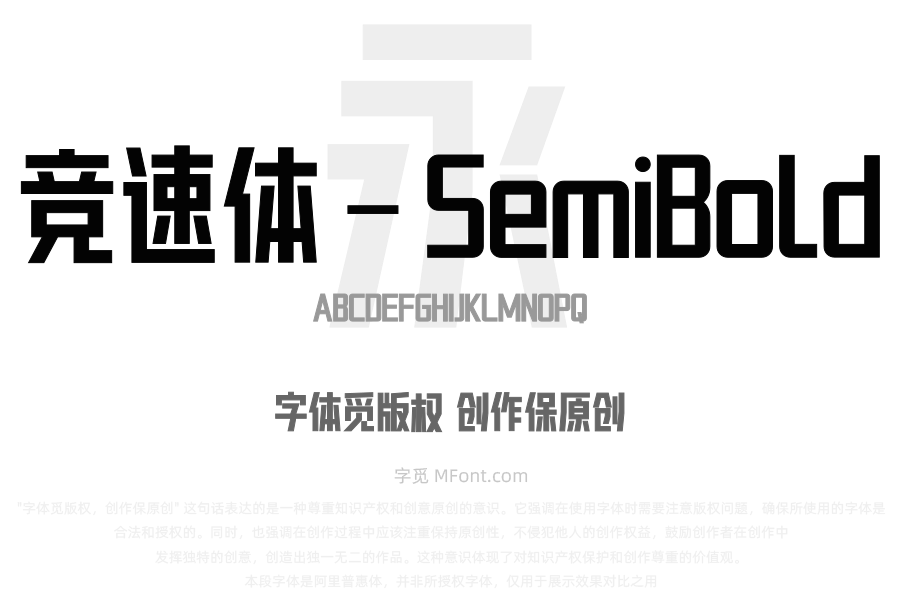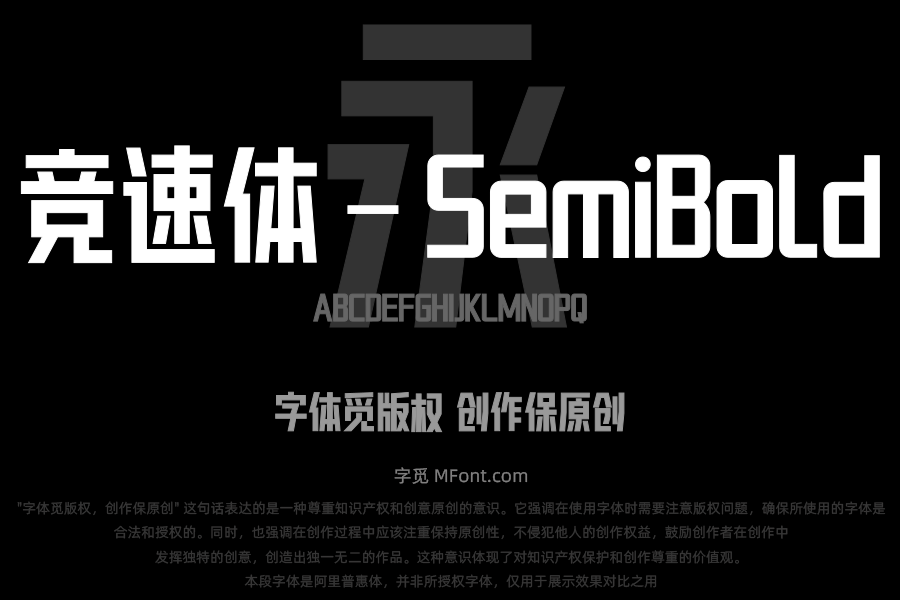
郑庆科竞速体-SemiBold
关于郑庆科竞速体-SemiBold字体字库信息
字体全名: 郑庆科竞速体-SemiBold
铸字厂: 庆科字体
设计师: 济南一字百炼艺术设计有限公司
字体简介: 郑庆科竞速体-共有4个字重,分别为:郑庆科竞速体-Bold、郑庆科竞速体-Medium、郑庆科竞速体-Regular、郑庆科竞速体-SemiBold。郑庆科竞速体-SemiBold是一款专门为体育运动开发的字体。适合各种运动赛事。本次巴黎奥运会来临之际,相约巴黎、祝愿中国队旗开得胜。中国队加油。